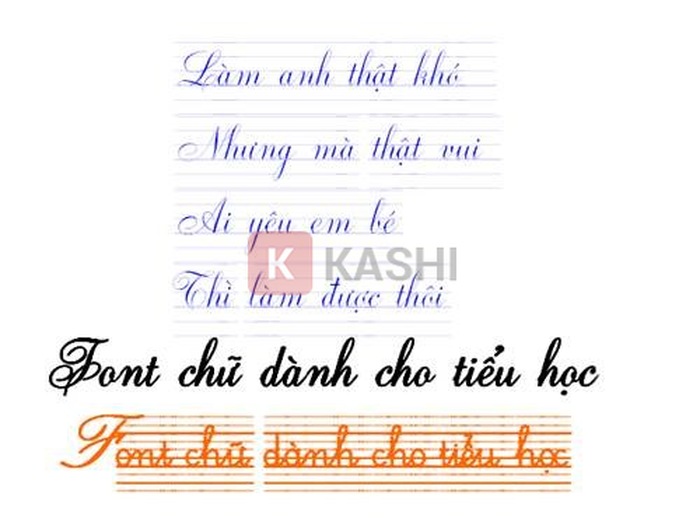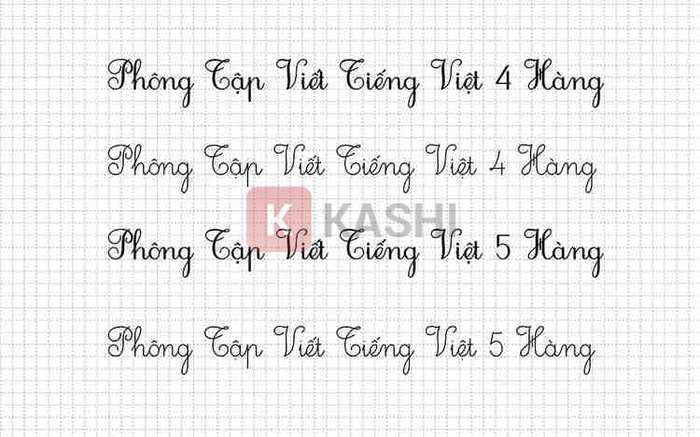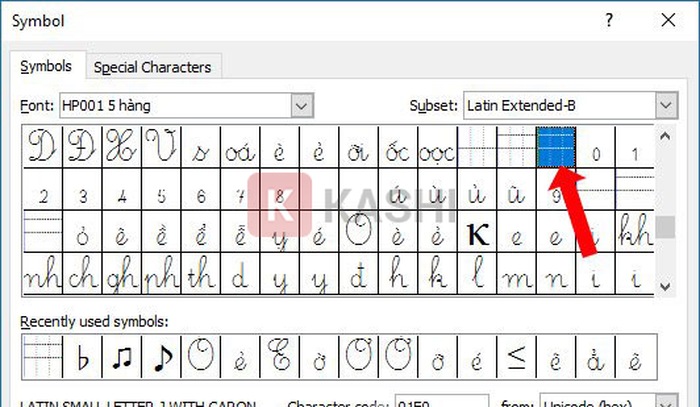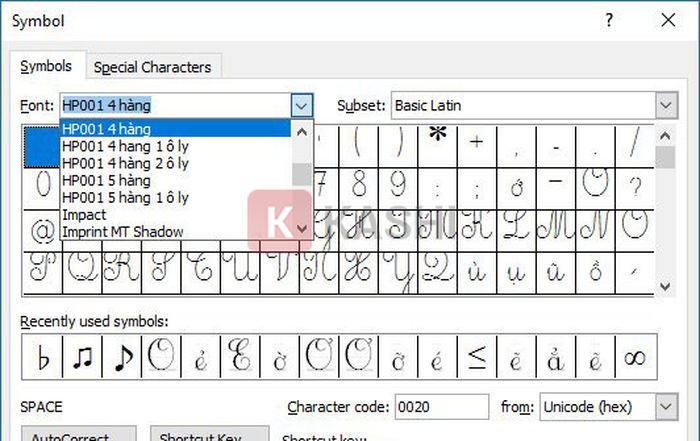
Font chữ tiểu học chuẩn là gì? Tải và cài đặt font chữ tiểu học viết tay có ô ly như thế nào? Bài viết này sẽ hướng dẫn chi tiết về font chữ tiểu học theo quy chuẩn của Bộ Giáo dục và Đào tạo, giúp thầy cô và phụ huynh có tài liệu chuẩn cho bé luyện viết.
Font Chữ Tiểu Học là gì?
Font chữ tập viết tiểu học là bộ font tiếng Việt chuẩn, hỗ trợ giáo viên soạn giáo án chính tả và giúp phụ huynh kèm con luyện viết tại nhà. Tương thích với Unikey và Vietkey, font chữ này được thiết kế trên giấy kẻ ô ly, gồm 26 chữ cái tiếng Việt chuẩn đẹp, bám sát sách giáo khoa và sách bài tập. Đây là font chữ phổ biến được nhiều giáo viên tiểu học áp dụng.
Tính Năng Nổi Bật của Font Chữ Tiểu Học
Font chữ tiểu học mang lại nhiều lợi ích:
• Cung cấp 19 font chữ tập viết chuẩn Bộ GD&ĐT.
• Mẫu luyện viết chữ đẹp cho học sinh tiểu học.
Các Loại Font Chữ Tiểu Học
Bộ font chữ tiểu học gồm 2 loại: 4 hàng và 5 hàng. Loại 4 hàng tương tự tập học sinh 4 ô ly nhưng chưa hỗ trợ đầy đủ ký tự (Ô, Ắ…). Bộ font bao gồm 4 file:
Mẫu Font chữ tiểu học
Font chữ tiểu học Full 2025